一部电影最好看的是内容,但是在观看内容之前,电影字体设计也非常重要,如果电影字体设计的比较好看,艺术表现力比较强,那么对于观众的吸引力就会很大。字体视界觉得想要把电影字体设计的更吸引人一点,那么一定要具备这些字体特点。
电影字体只是字体当中的一种,但却是我们生活当中最常见的一种字体。要知道字体并不是凭空出现的,之所以会有不同的字体,是因为人对于艺术表现的不同追求与欣赏,这造成了字体不断的延伸和变化,所以现在我们使用的字体种类比较多,每一种字体都有各自的特点。
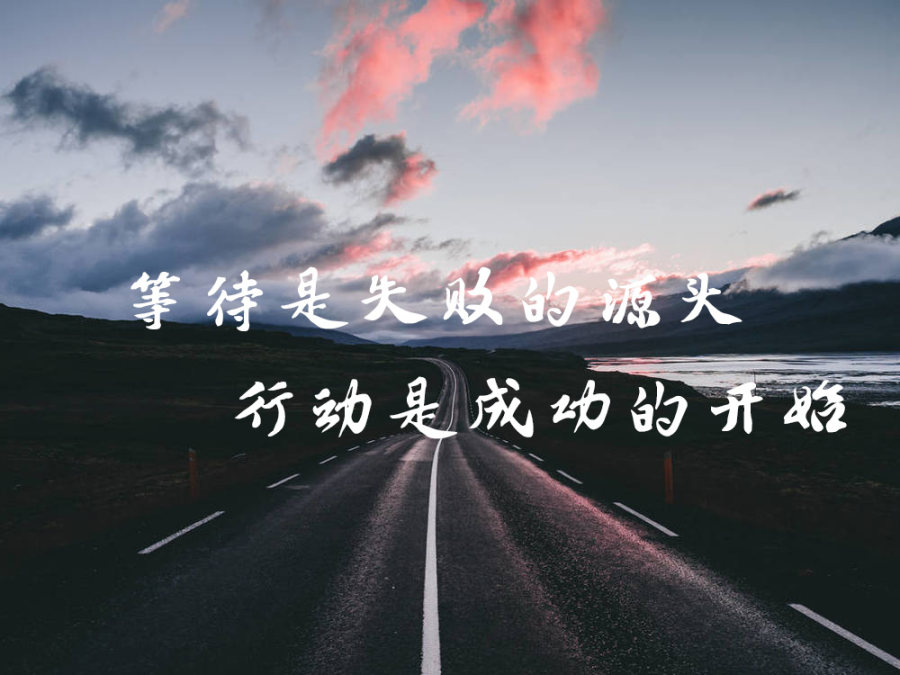
影视字体的设计风格也比较多,一般比较常见的字体风格,要么是秀丽柔美的,要么是给人稳重挺拔的感觉,或者是带有一丝活泼有趣的视觉效果,而电影字体使用比较多的就是苍劲古朴。不同题材的电影,在选择电影字体的时候也会有所不同,有些喜剧效果比较浓郁的电影就会选择活泼有趣的字体,这样会给观众带来喜感,能够很好的表达出电影的风格。
电影字体的设计并不是很难,想要做电影字体字库本身也不困难,只要利用一些专门的字体设计软件就可以很轻松的完成对字体的设计。但字体视界认为,字体设计的时候也需要注意字体的特点,对于一些刚刚学习做字库的人来说,首先应该从中文字库当中导出国标二级字库的字形图片,然后将这些图片作为试验的字模,最后就可以通过直接导入到专业的字体设计软件上形成字库文件,这样就可以在原本的字体造型基础上,对这个字体再进行修改,经过字体的修改之后就能够设计出很多不同风格的字模板。